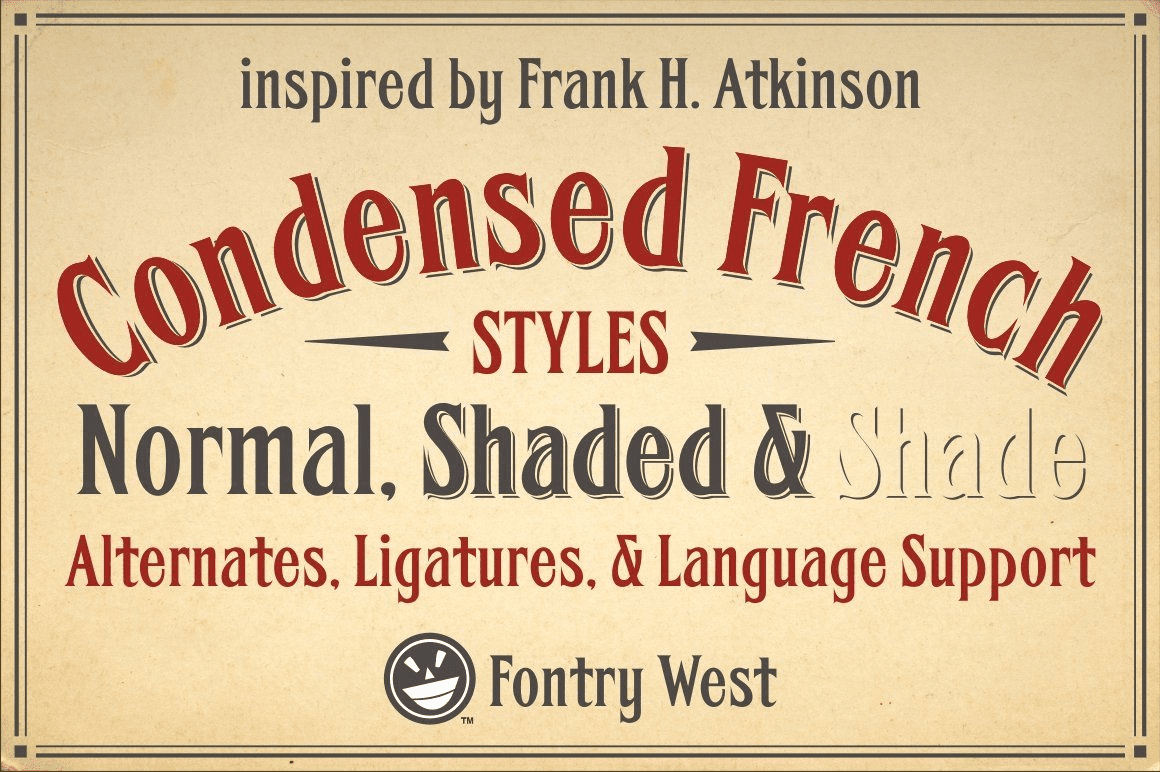
Можно предположить, что FHA Condensed French, вероятно, начинал свою жизнь как древесина для дисплеев, заголовков и плакатов. Преувеличенные острые засечки и конденсированные формы не были редкостью в этот период. В какой-то момент знаковые художники подхватили Condensed French, добавив свой собственный характер. В конце XIX века Фрэнк Х. Аткинсон включил конденсированный французский язык в образцы надписей для своей книги "Живопись знаков - полное руководство". Эта книга стала одним из окончательных руководств по написанию знаков и ручных надписей. В 1999 году Майк Адкинс оцифровал Condensed, чтобы добавить его в коллекцию Аткинсона.